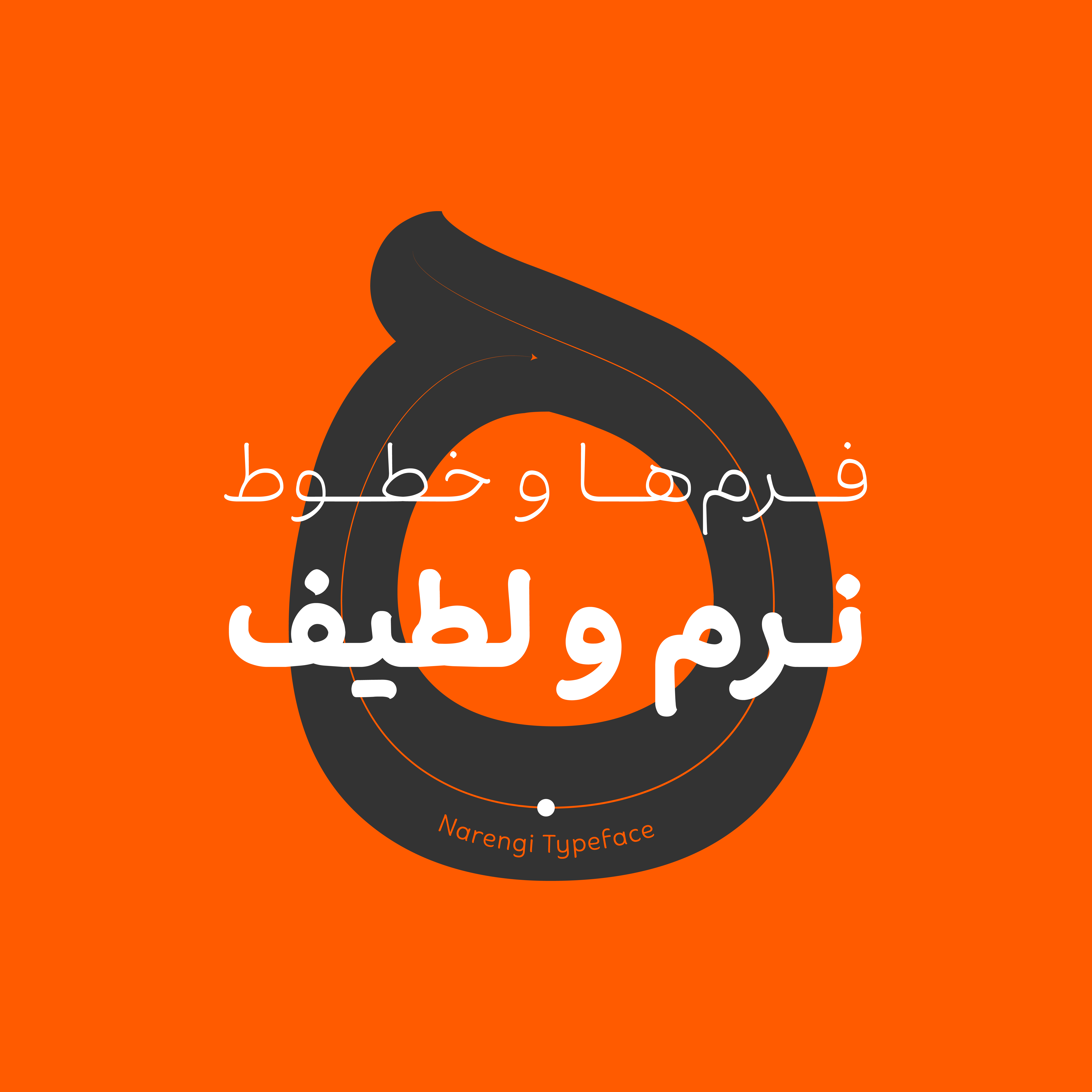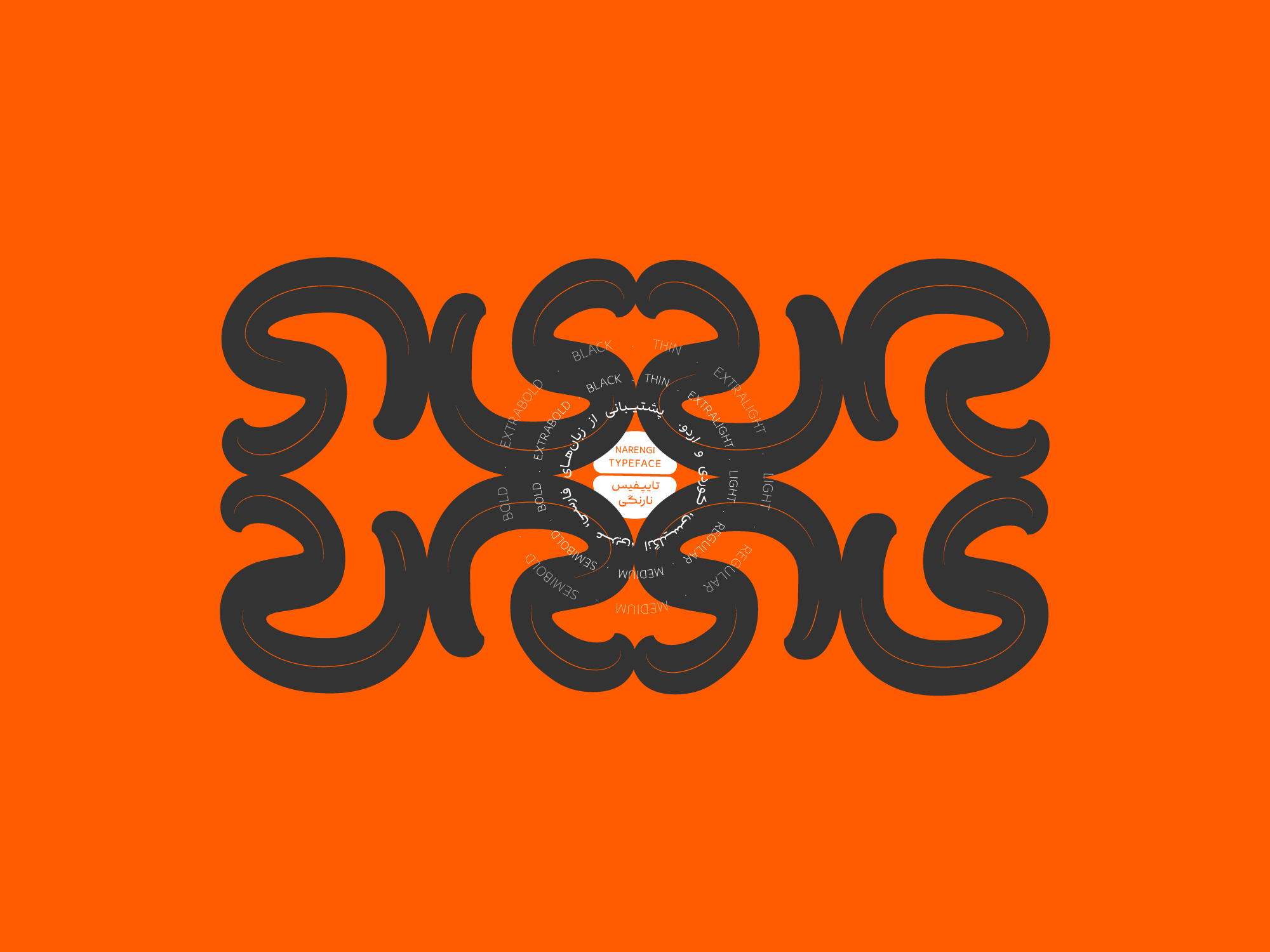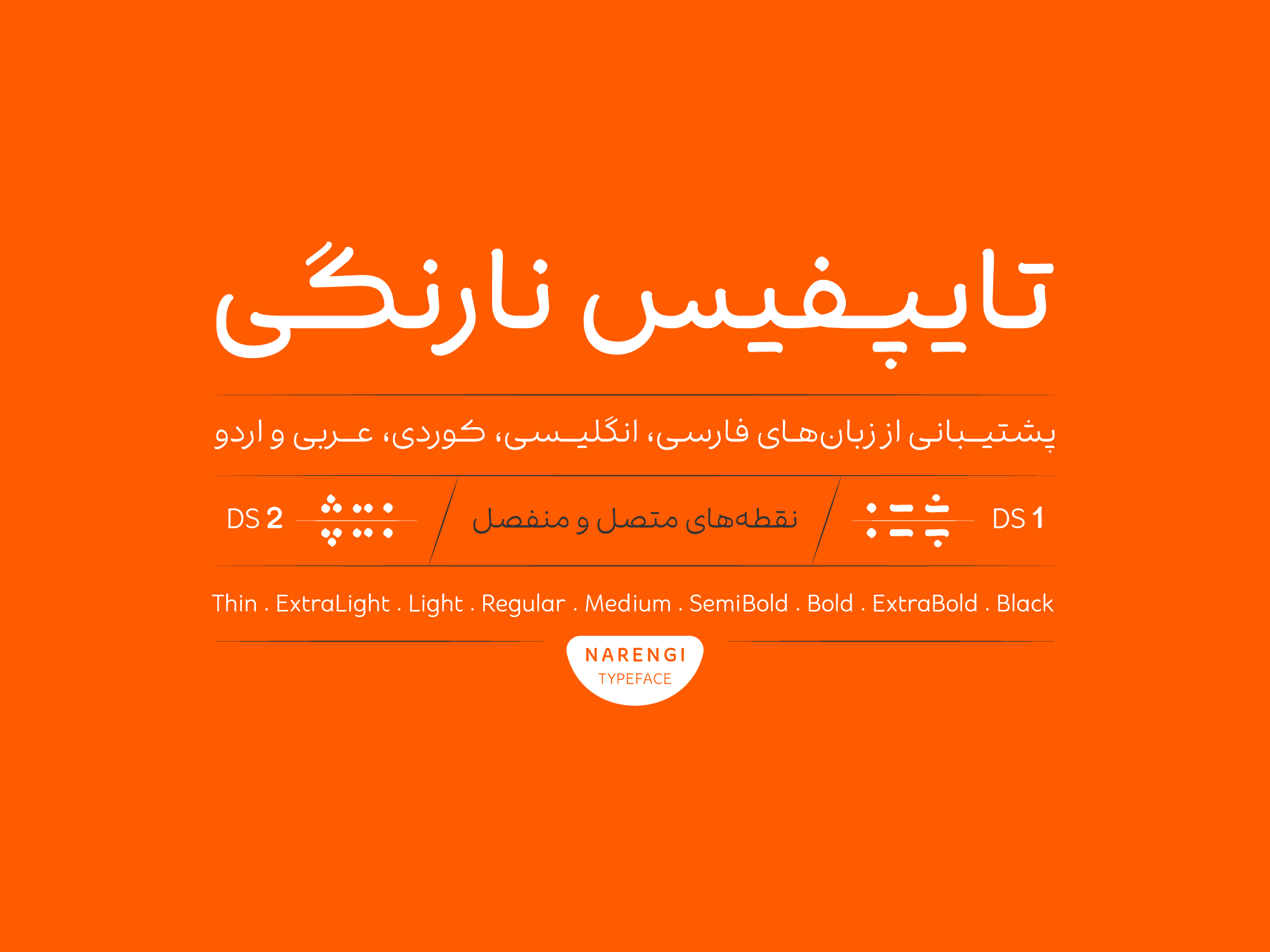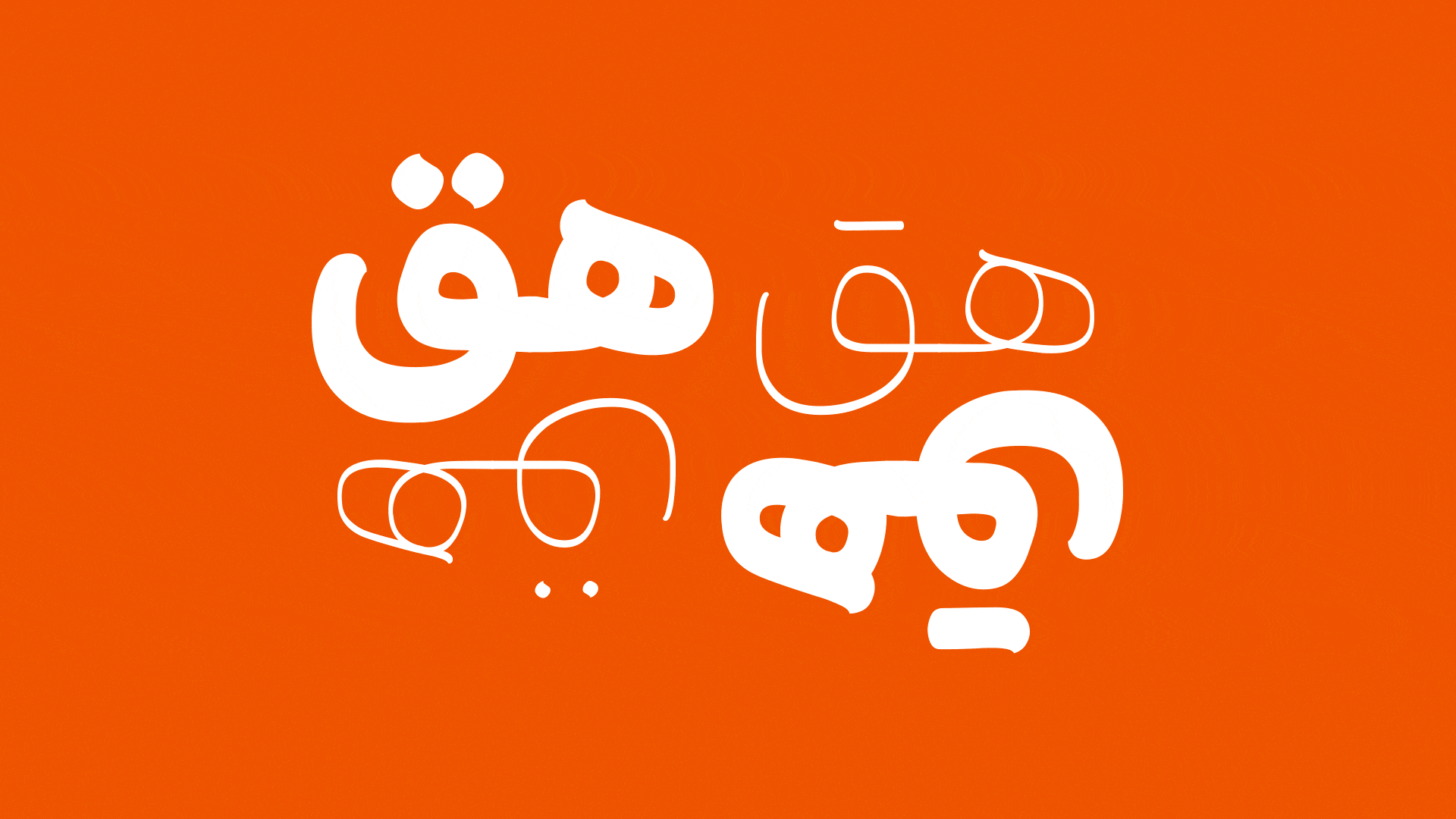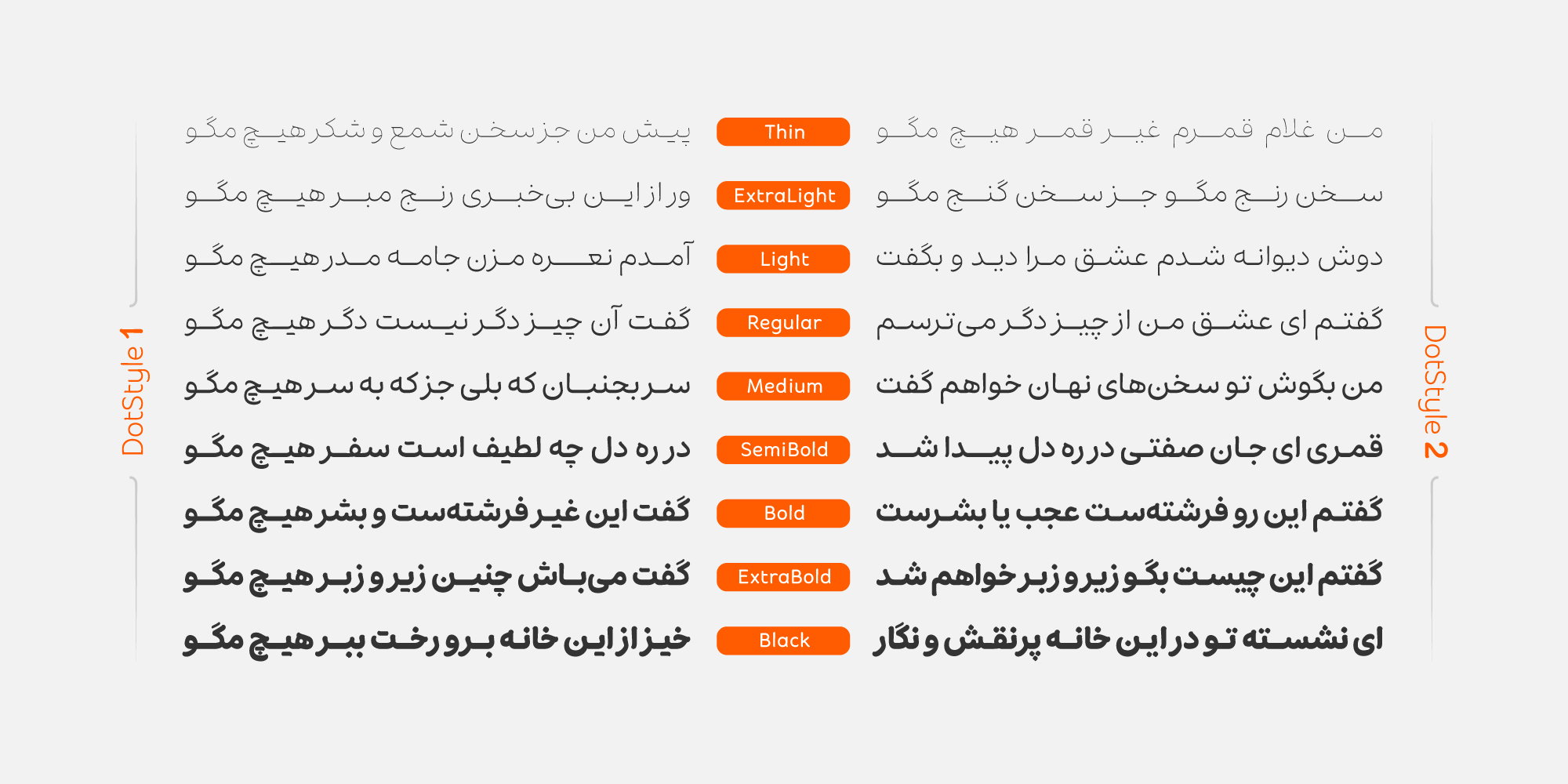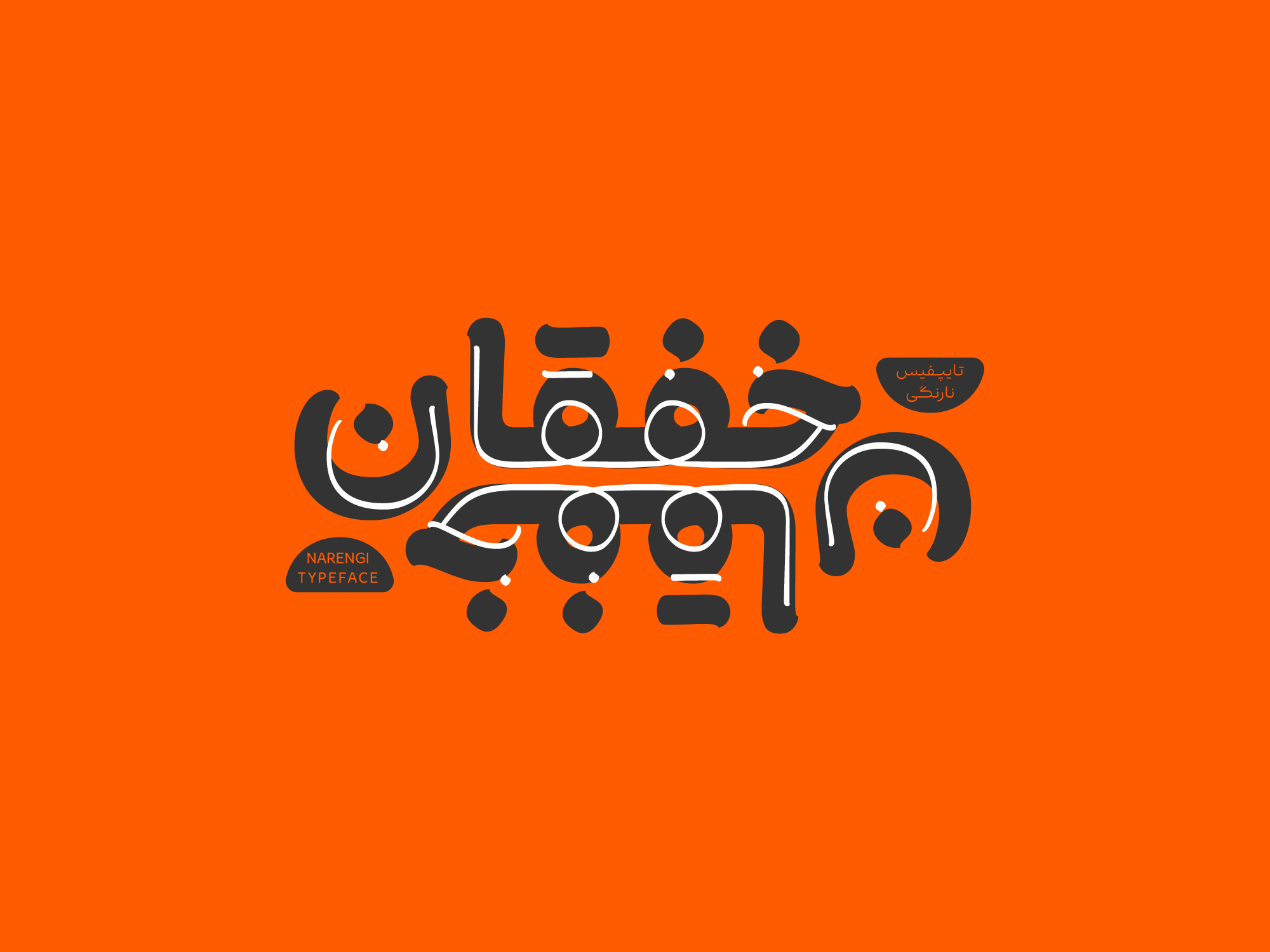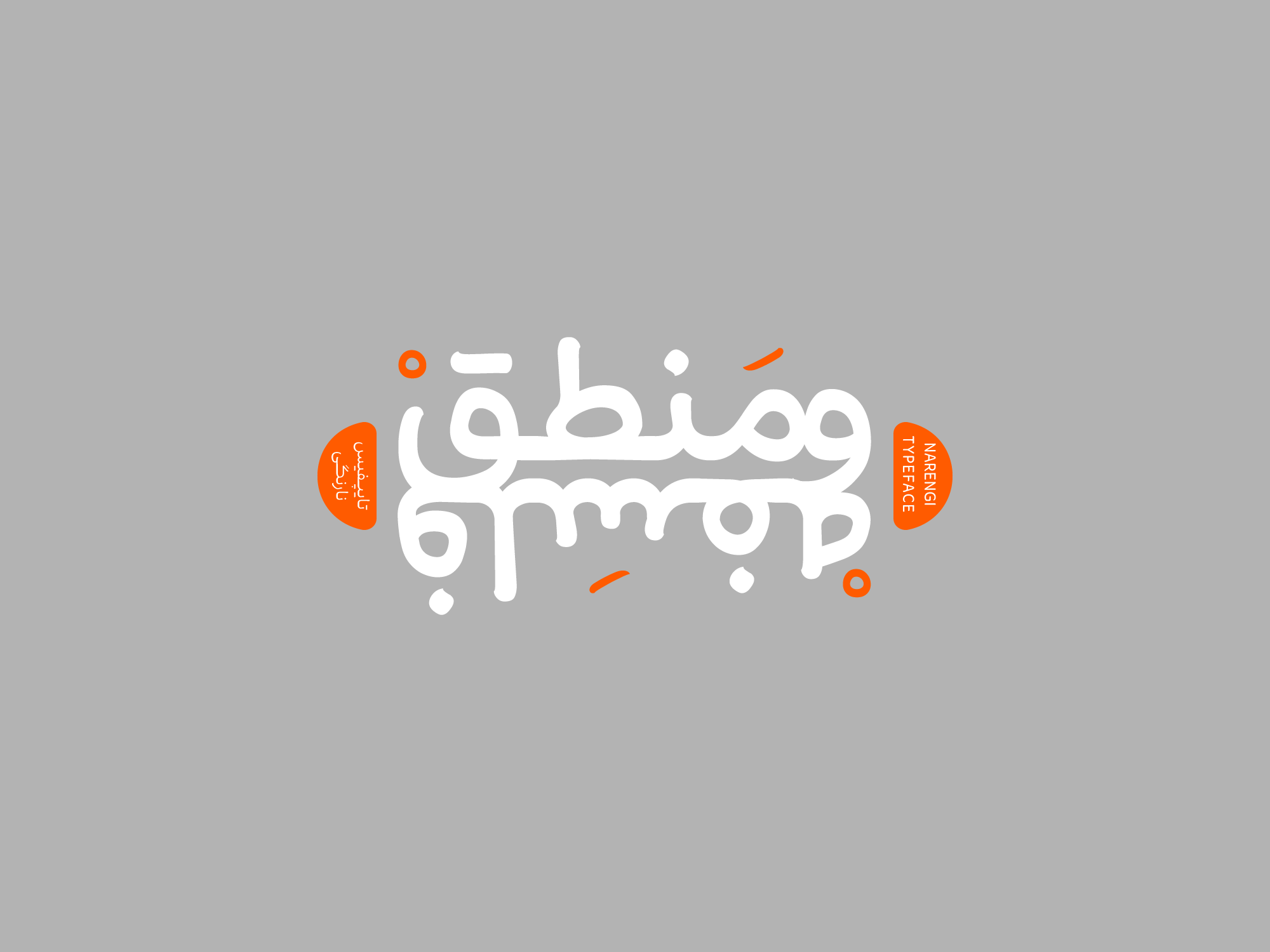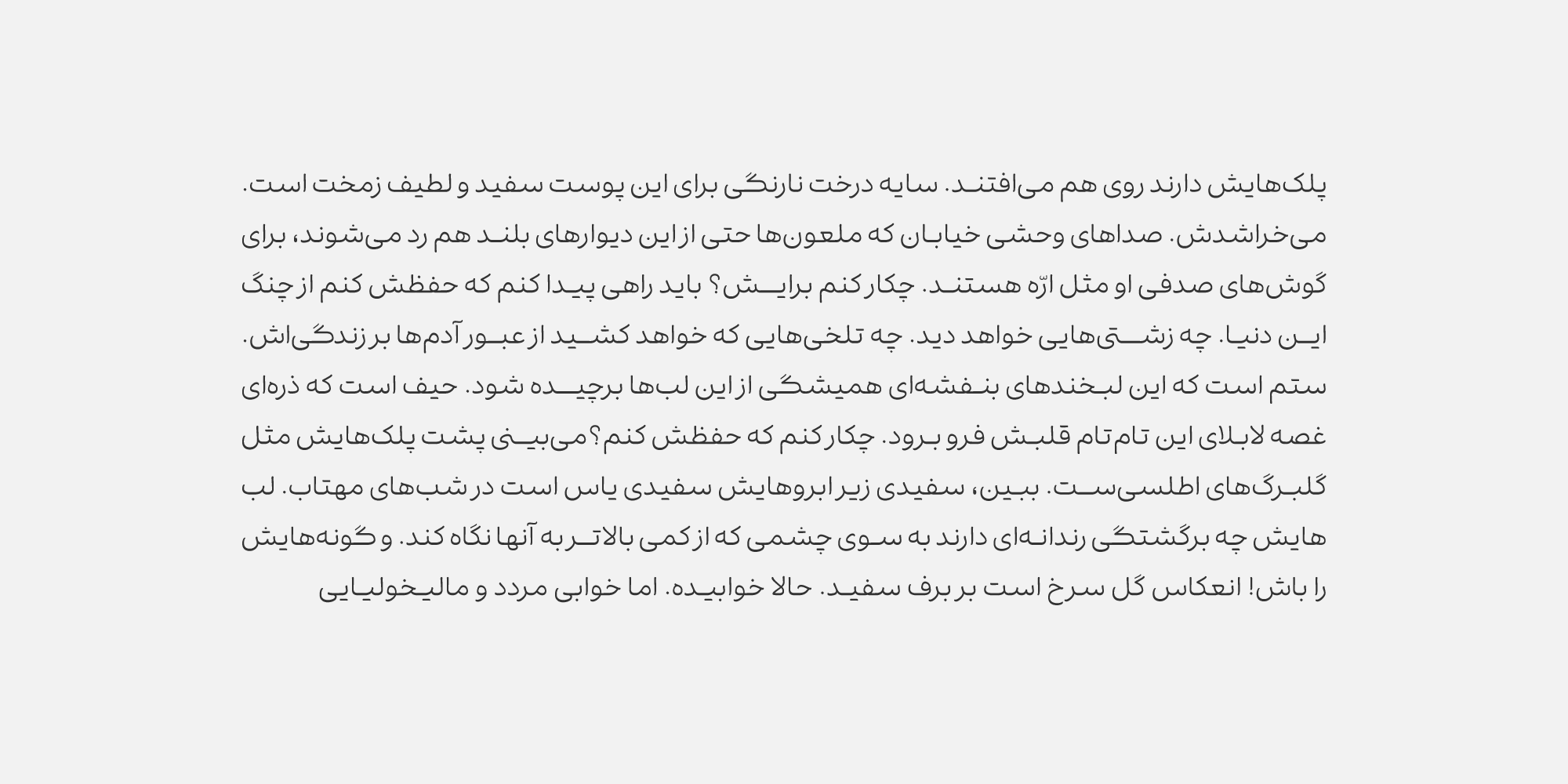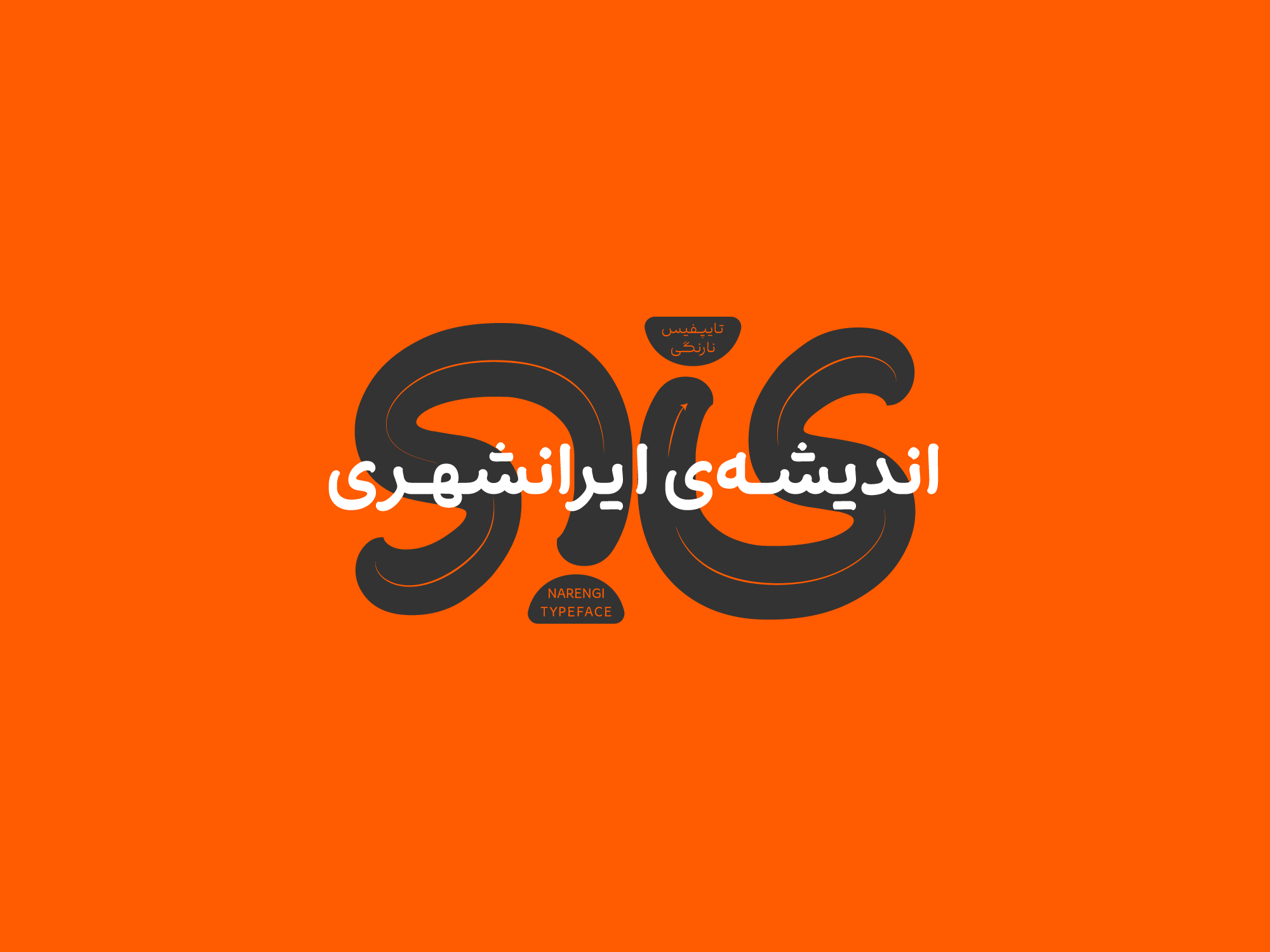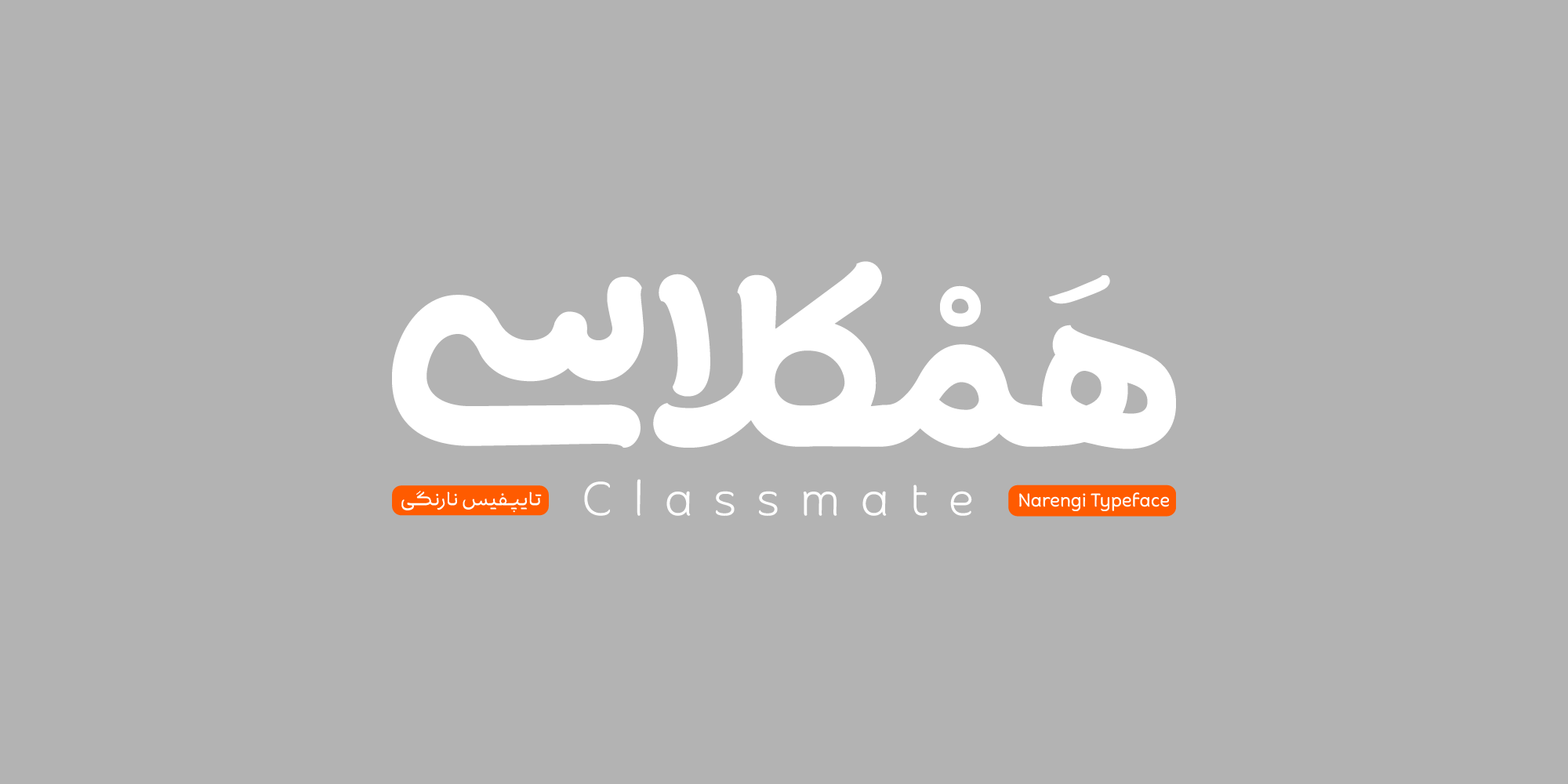
فونت نارنگی در ۹ وزن متنوع طراحی شده، از دو استایل متفاوت برای نقطهها (متصل و منفصل DS1 & DS2) بهره میبرد و از زبانهای فارسی، انگلیسی، کوردی، عربی و اردو پشتیبانی میکند.
فونت نارنگی در برخی حروف آن کشیدگیهای مشخصی دیده میشود و در مجموع، نسبت به سایر فونتهای فارسی، کشیدگی عرضی بیشتری روی خط کرسی دارد.
انتخاب این فرم از حروف و گنجاندن این کشیدگیها بر پایه چند دلیل فنی و بصری انجام شده است: نخست، انعکاس ساختار آوایی زبان فارسی در ساختار بصری فونت؛ دوم، الهام از کشیدگیهای خط نستعلیق برای ایجاد ریتم در نوشتار و پرهیز از یکنواختی بصری؛ و سوم، ایجاد تعادل و نظم در کنار منحنیها و دورهای متعددی که هم در استخوانبندی و هم در فرم کلی حروف وجود دارند.
عملکرد فونت متناسب با وزن و کاربرد آن تفاوت دارد؛
در وزنهای پایین که مناسب استفاده در متن هستند، حضور این کشیدگیهای عرضی، سکون و تعادلی بصری در برابر انحناهای زیاد حروف ایجاد میکند و از بهم ریختگی متن جلوگیری میکند.
در مقابل، در وزنهای سنگینتر و کاربردهای تیتری، این کشیدگیهای عرضی کاهش یافتهاند تا امکان نمایش کلمات درشتتر در فضای محدود فراهم شود.
با فعال کردن set1 در قسمت opentype کشیدگیهای پیشفرض برخی حروف و لیگیچرها از بین میرود.